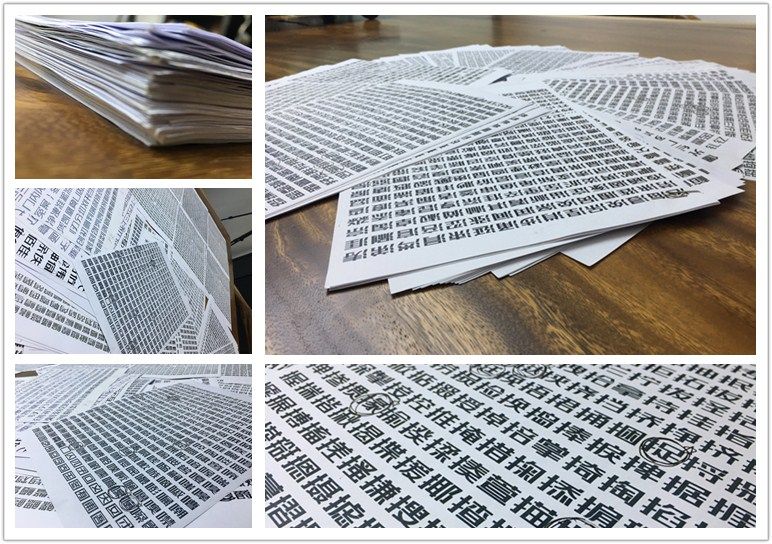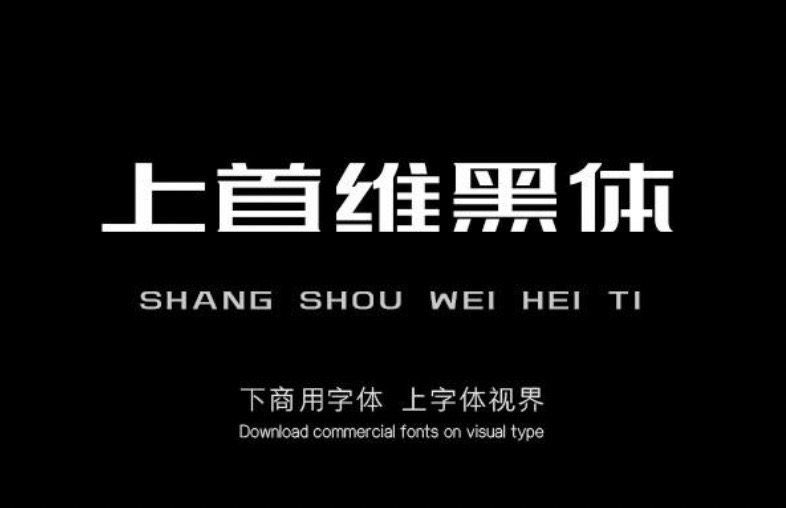
上首造字
字体名字:上首维黑体
一、维黑体起因
商业广告中,文字是传播最直接的载体,字体变形在设计页面中的比列不容忽视,在设计的工程中,我们经常需要去选择字体,面对千千万万的系统字体我们会浪费很多时间。
慢慢的,面对标志设计用户群体的总体侧重,开发的一款多应用于标题的基础字体。在品牌标志、标题、重点强调等方面能够直接被应用,也便于企业和设计团队的选择。适用于搭配标志、广告标语、商业广告等高端属性。这样一来,不仅快捷,在字体上也有了设计感。
二、维黑体创作过程
三、关于维黑体
亮点:字体风格稳重呈方块形,字体笔画竖折处细节处理
印象:厚重、有力、方正、坚韧、稳健,可靠
感觉:坚毅而又并非冷峻